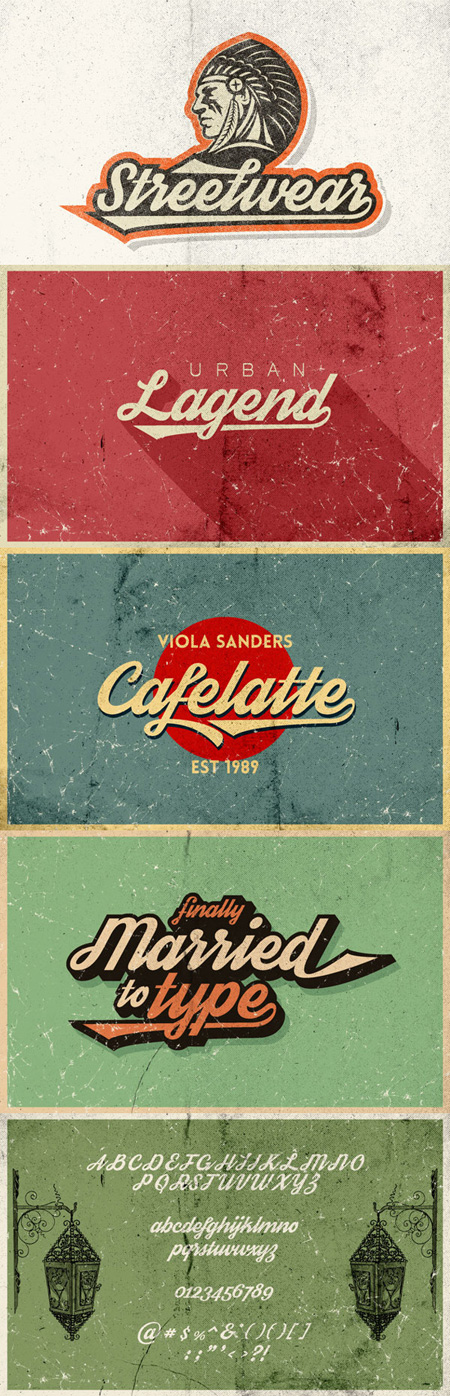
Классный шрифт!
эм, а где эти хвостики на буквах?
Без курсива нет?
Как сделать хвостик на букве Y ??? Подскажите пожалуйста,.....и еще как сделать такую тень и обводку?
где взять этот длинный хвостик?
Я новичок в ФТШ, подскажите мне пожалуйста, вот в конце как делать эту "стрелочку" , а то у меня просто буква
Это уже дорисовали)